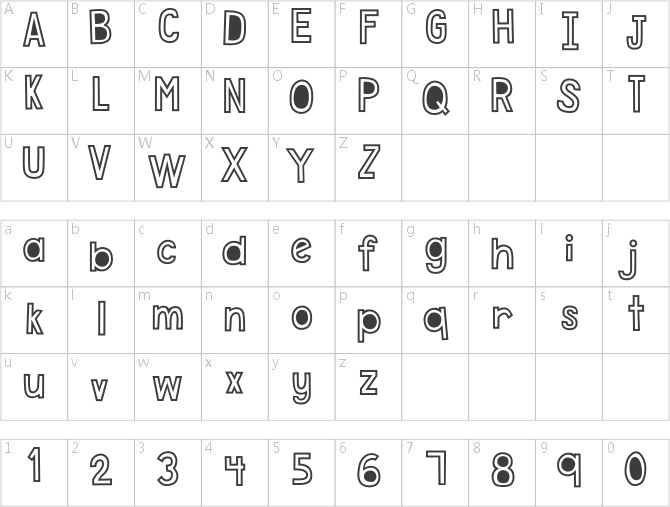
DJB Just Don't Call Me Crazy 詳情頁
DJB Just Don't Call Me Crazy
DJB Just Don't Call Me Crazy介紹
DJB Just Don't Call Me Crazy字體字庫是一款讓人賞心悅目、百看不厭的英文字體,適合各類廣告和產品包裝設計應用,字體大小0.05MB,格式為ttf字體,上傳用戶是瀨子,作者/版權方為未知
DJB Just Don't Call Me Crazy效果圖